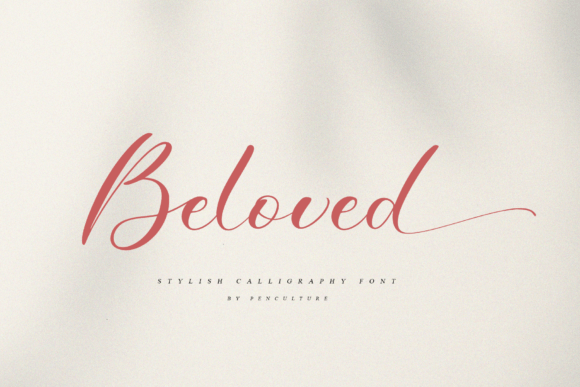
Beloved
Si buscas recursos de alta calidad como Beloved, este paquete premium es una opción fantástica para tus proyectos creativos.
Ya sea que estés creando productos POD (impresión bajo demanda), invitaciones de boda o gráficos para redes sociales, Beloved es una opción ideal.